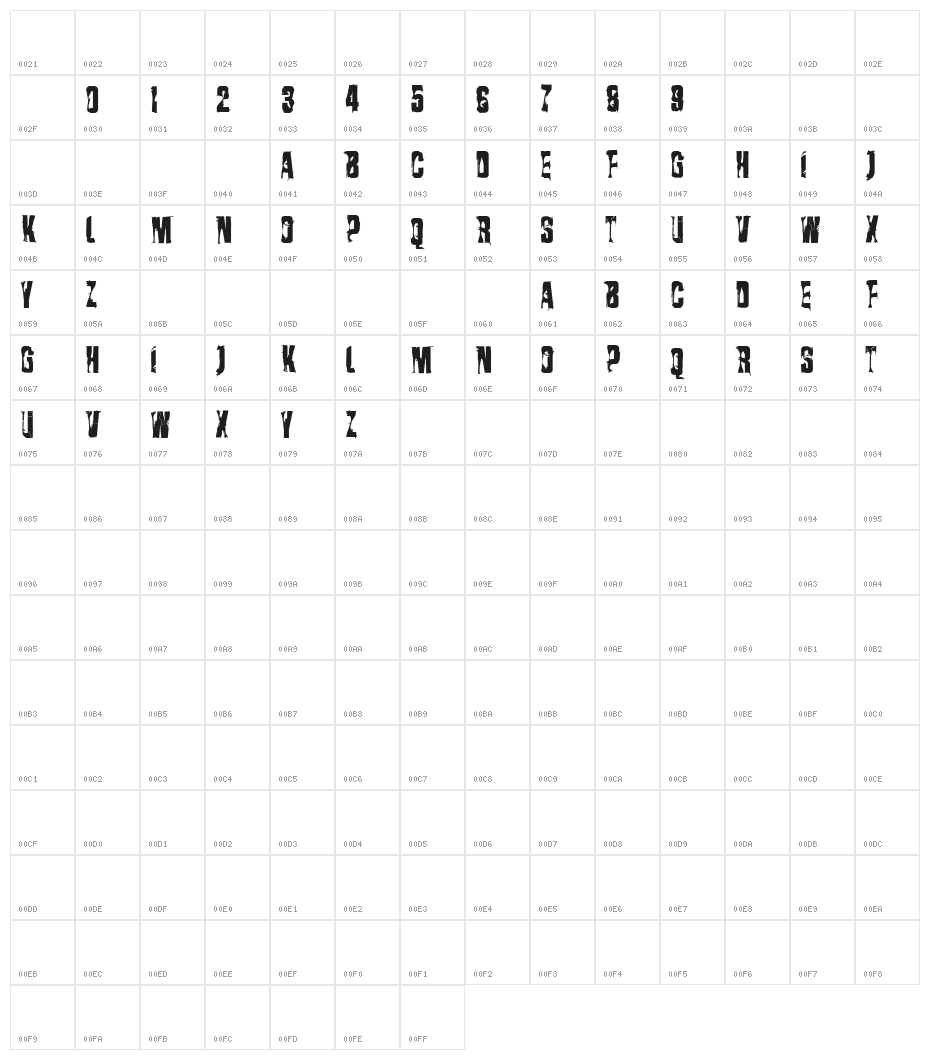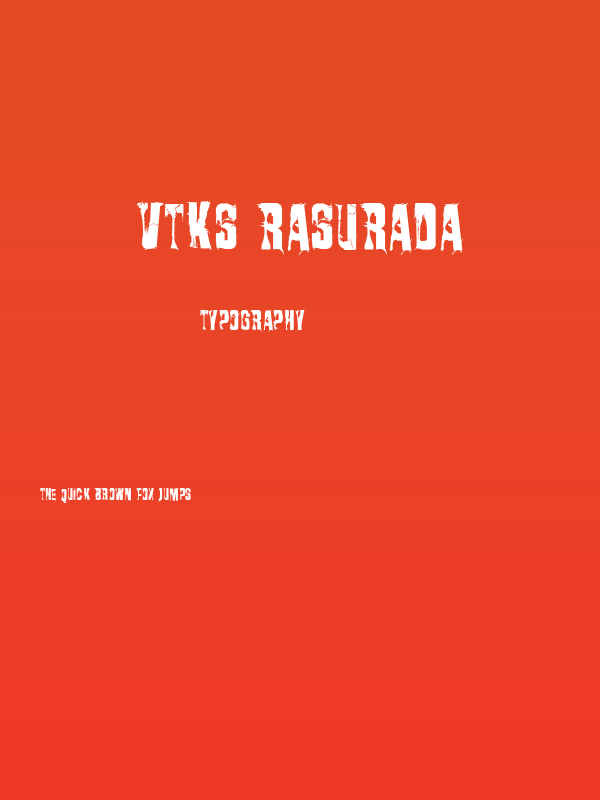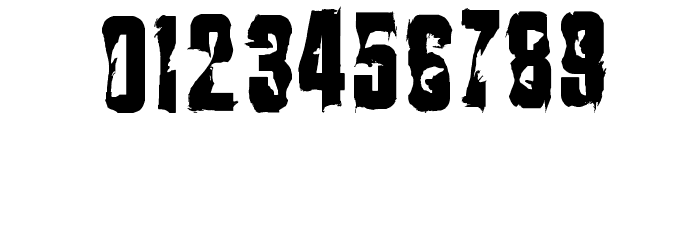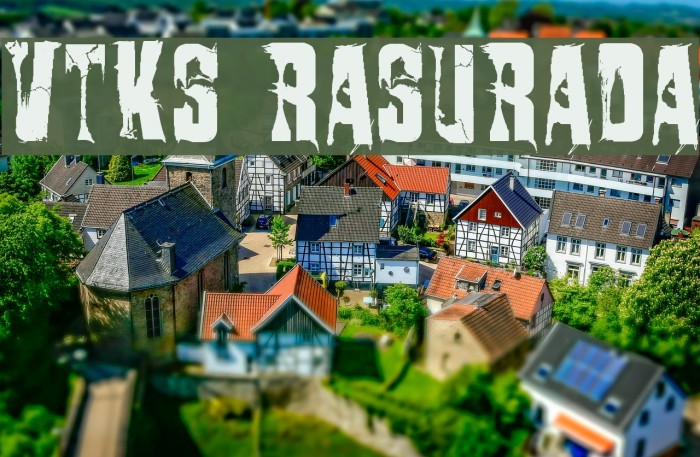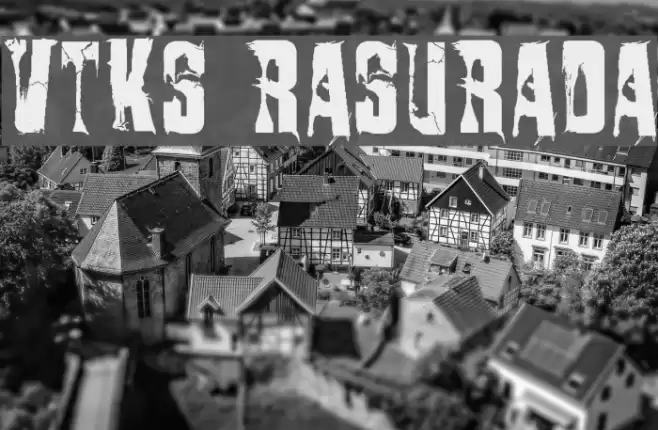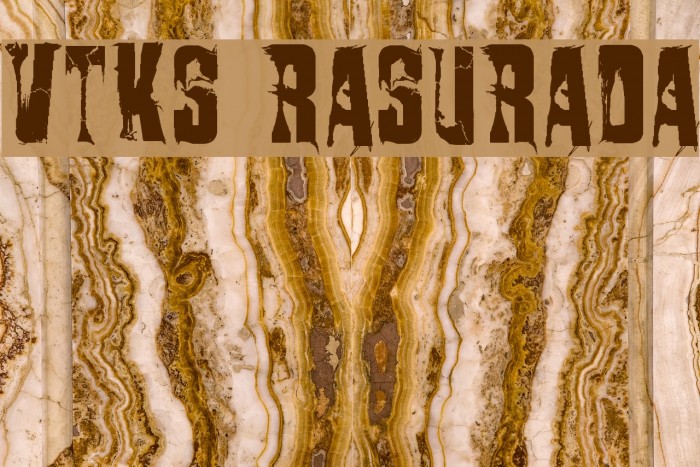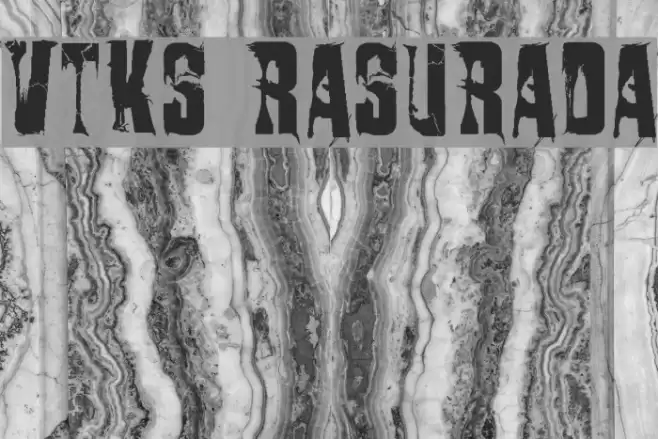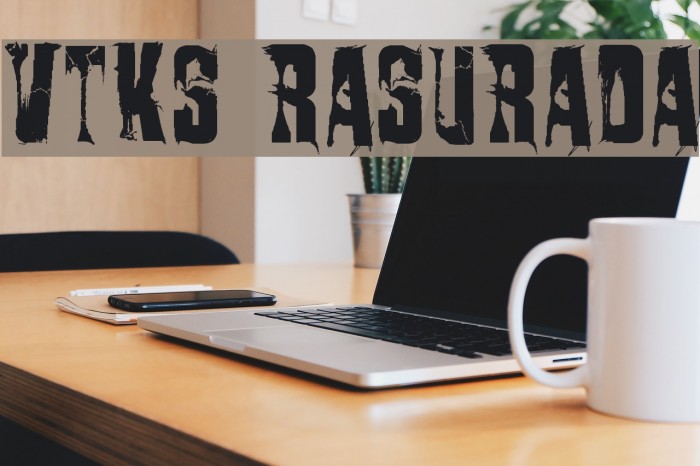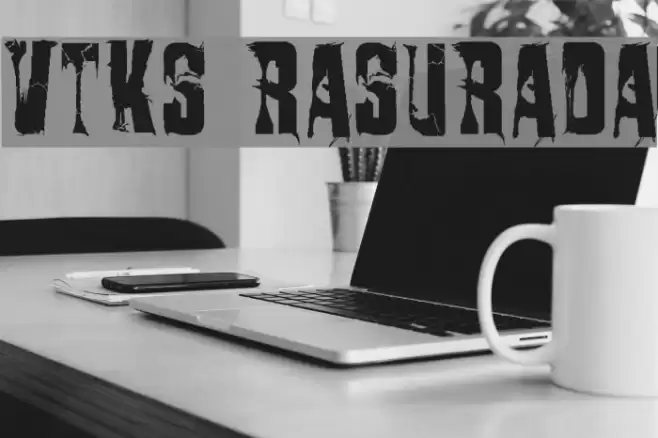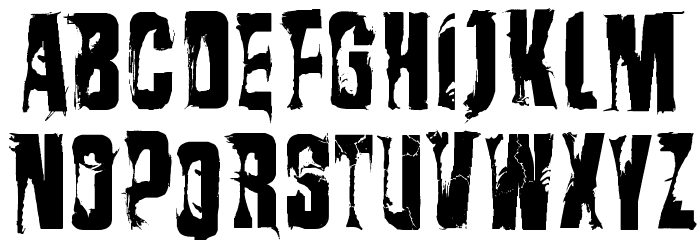
VTKS RASURADA Font
✎ Distorted Eroded
| Style général | Edgy, Grunge |
| Projets proposés | Ideal for album covers, horror movie posters, edgy branding, and streetwear designs. |